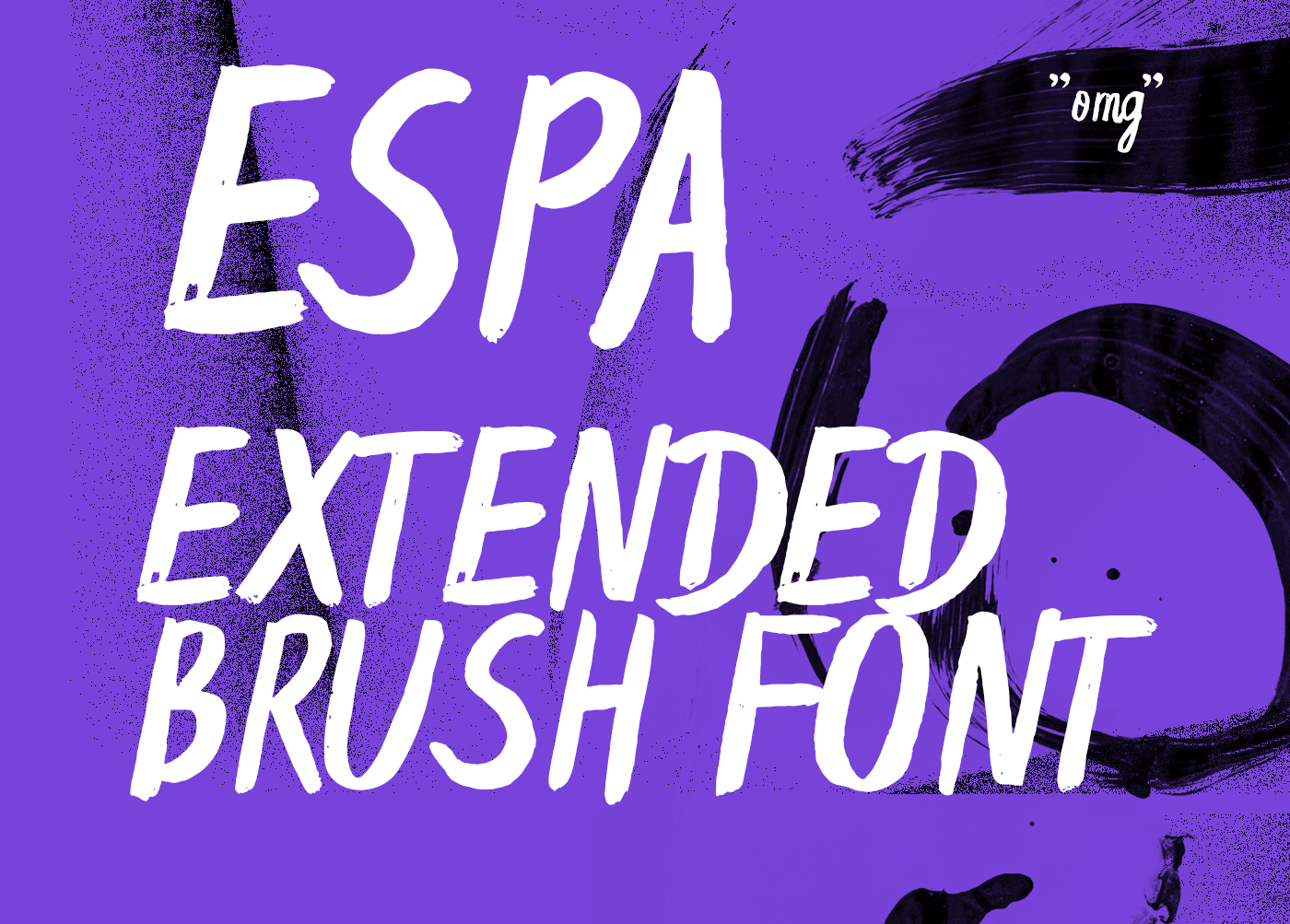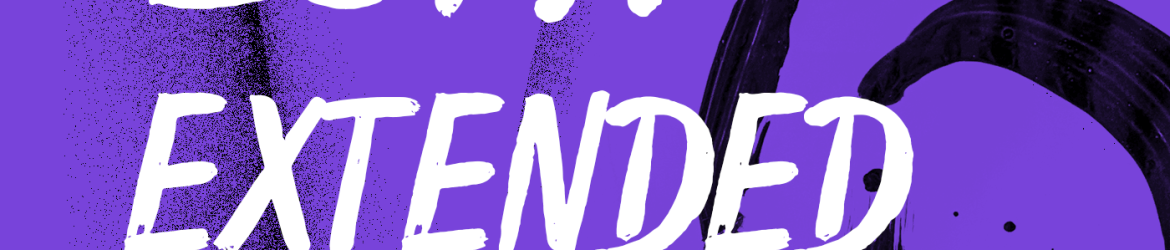
Espa Extended Brush é uma nova fonte que traz à sua coleção de fontes algo inovador e único. Ideal para quem busca adicionar uma camada de personalidade a seus projetos digitais, este estilo de tipo foi criado pelo designer Krišjānis Mežulis. O Espa Extended possui um traço feito para sentir-se ao mesmo tempo sofisticado e familiar, inspirando-nos à lembrança da arte manual do desenho na água. Este tipo feito com uma caneta de pincel fina sobre papel acrílico dá vida a cada letra, criando uma textura única e vibrante. O Espa Extended oferece suporte para o alfabeto latino estendido e grego, assim como o alfabeto cirílico. Adicionar Espa Extended Brush à sua coleção de fontes é investir em algo que não apenas complementará seu design gráfico, mas também contribuirá com uma sensação artística e autêntica aos seus trabalhos.